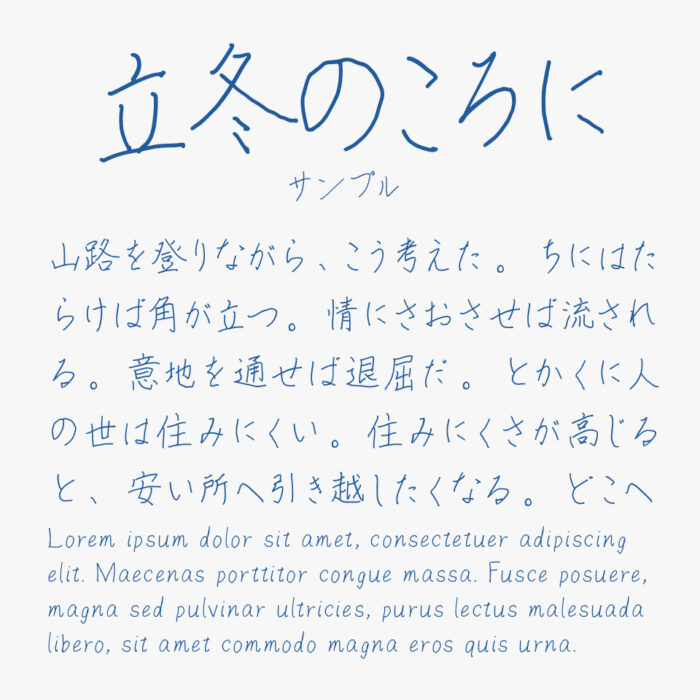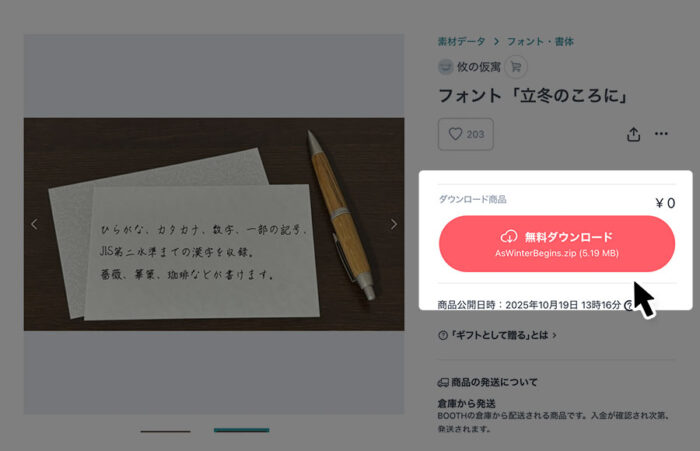
立冬のころにフォントは、攸の仮寓さんによるやさしさと素朴さを感じさせる手書きフォントです。
ボールペン字のような細めのラインと、文字のかすれや揺らぎがあり、筆圧の変化や自然な書き癖がそのまま再現されている手書き文字です。リズムが心地よく、読んでいるだけで、どこか季節の移ろいや人のぬくもりが伝わってくる手書きフォントです。
漢字もJIS第二水準まで収録されているので、「薔薇」「篳篥」「珈琲」など難しい漢字なども使用できます。
| 漢字 | ○(JIS第二水準まで) |